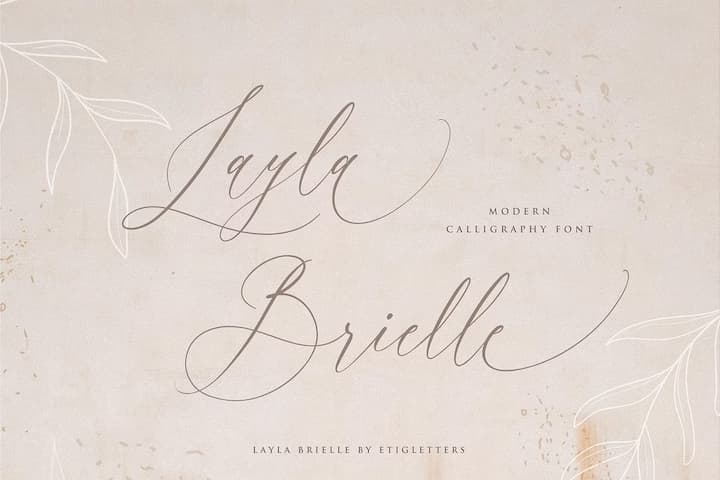
Layla Brielle
典型的なモダンカリグラフィースクリプト。これといった特徴はないが(笑)最近は流行も落ち着いたようであまり新作は出ていないので、久しぶりにこのタイプを紹介してみた。大文字にはオルタネートはないが、小文字には小さなスワッシュとビギニング/エンディングストロークの付いたオルタネートがあるので、多少のバリエーションは作れる。ま、安いので気軽に使えるかな。1ウェイトのみ。